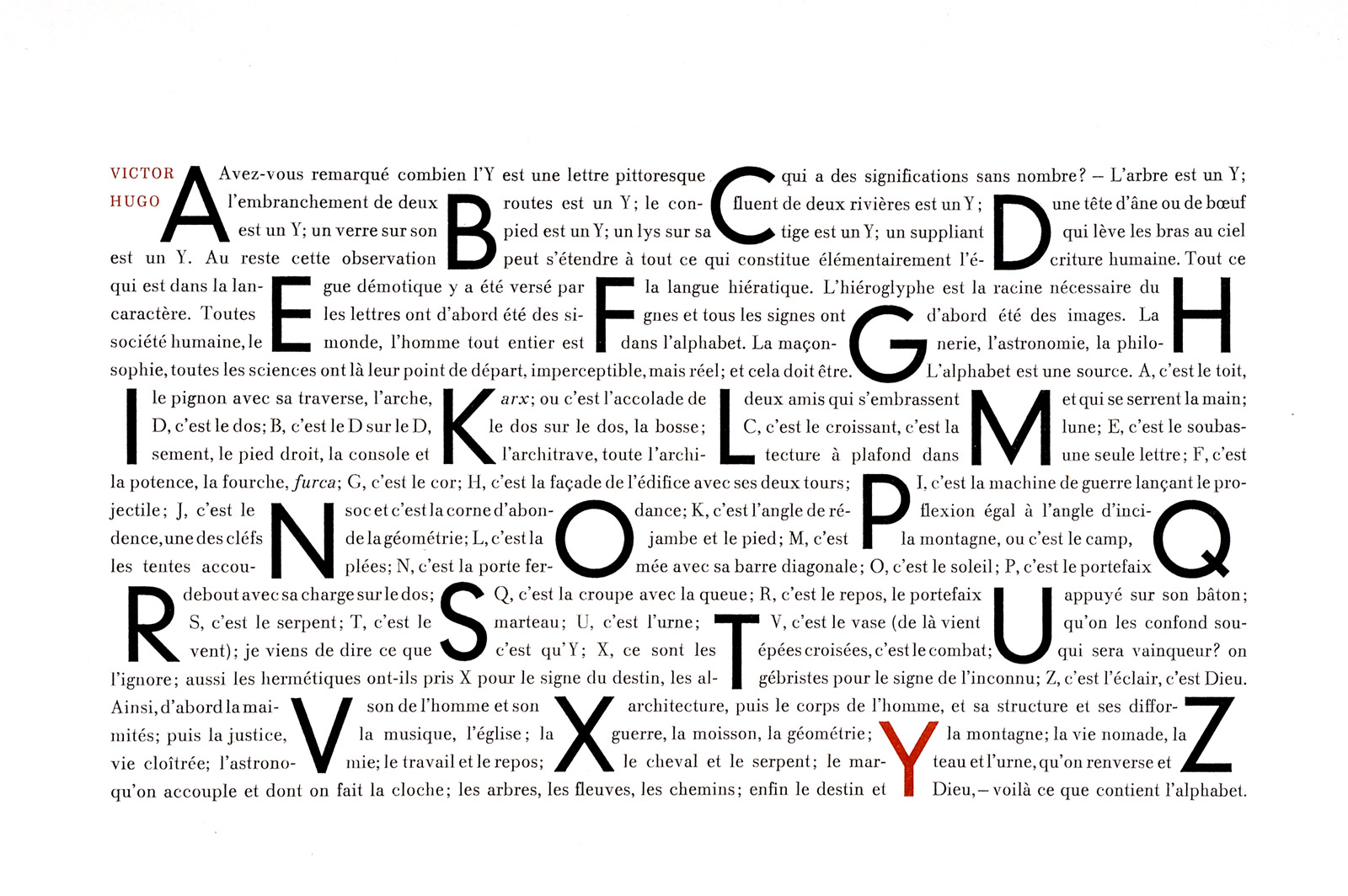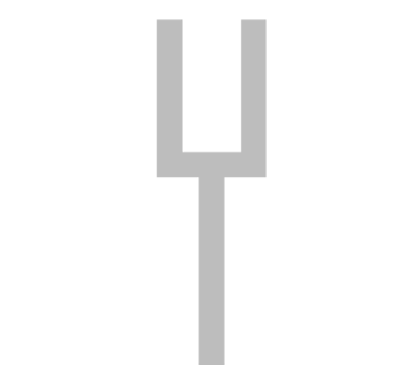
A, B, C, X, Y, Z | signes et symboles
Avez-vous remarqué combien l’Y est une lettre pittoresque qui a des significations sans nombre? — L’Arbre est un Y; l’embranchement de deux routes est un Y; le confluent de deux rivières est un Y; une tête d’âne ou de bœuf est un Y; un verre sur son pied est un Y; un lys sur sa tige est un Y; un suppliant qui lève les bras au ciel est un Y. Au reste cette observation peut s’étendre à tout ce qui qui constitue élémentairement l’écriture humaine. Tout ce qui est dans la langue démotique y a été versé par la langue hiératique.
L’hiéroglyphe est la racine nécessaire du caractère. Toutes les lettres ont d’abord été des signes et tous les signes ont été d’abord des images. La société humaine, le monde, l’homme tout entier est dans l’alphabet. La maçonnerie, l’astronomie, la philosophie, toutes les sciences ont là leur point de départ, imperceptible, mais réel; et ce la doit être. L’alphabet est une source. A, c’est le toit, le pignon avec sa traverse, l’arche, arx; ou c’est l’accolade de deux amis qui s’embrassent et qui se serrent la main; D, c’est le dos; B, c’est le D sur le D, le dos sur le dos, la bosse; C, c’est le croissant, c’est la lune; E, c’est le soubassement, le pied droit, la console et l’architrave, toute l’architecture à plafond dans une seule lettre;
F, c’est la potence, la fourche, ƒurca; G, c’est le cor; H, c’est la façade de l’édifice avec ses deux tours; I, c’est la machine de guerre lançant le projectile; J, c’est le soc et c’est la corne d’abondance; K, c’est l’angle de réflexion égal à l’angle d’incidence, une des clefs de la géométrie; L, c’est la jambe et le pied; M, c’est la montagne, ou c’est le camp, les tentes accouplées; N, c’est la porte fermée avec sa barre diagonale; O, c’est le soleil; P, c’est le portefaix debout avec sa charge sur le dos; Q, c’est la croupe avec la queue; R, c’est le repos, le portefaix appuyé sur son bâton; S, c’est le serpent; T, c’est le marteau; U, c’est l’urne; V, c’est le vase (de là vient qu’on les confond souvent);
je viens de dire ce que c’est qu’Y ; X, ce sont les épées croisées, c’est le combat; qui sera vainqueur? on l’ignore; aussi les hermétiques ont-ils pris le X pour le signe du destin, les algébristes pour le signe de l’inconnu; Z, c’est l’éclair, c’est Dieu. Ainsi, d’abord la maison de l’homme et son architecture, puis le corps de l’homme, et sa structure et ses difformités; puis la justice, la musique, l’église; la guerre, la moisson, la géométrie; la montagne; la vie nomade, la vie cloîtrée; l’astronomie; le travail et le repos; le cheval et le serpent; le marteau et l’urne, qu’on renverse et qu’on accouple et dont o fait la cloche; les arbres, les fleuves, les chemins; enfin le destin et Dieu, — voilà ce que contient l’alphabet.
Victor Hugo